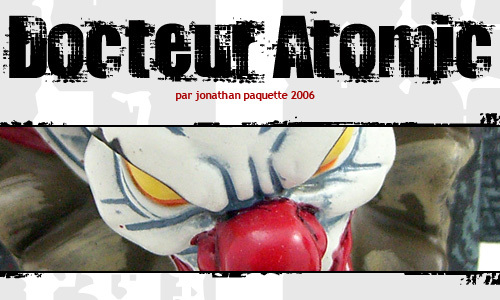
Krój Docteur Atomic od Jonathana Paquette'a uderza jak piaskowany tusz – wyraziste, blokowe litery z poszarpanymi przerwami, wytartymi krawędziami i zużytą teksturą, która sprawia wrażenie industrialnej, a nawet lekko radioaktywnej. To darmowy, erodowany font typu display, którego poszarpana powierzchnia nadaje nagłówkom historii bez potrzeby stosowania dodatkowych efektów postarzania.
Dzięki Docteur Atomic Twoje słowa stają się głośniejsze i bardziej surowe: plakaty koncertowe, ziny, okładki płyt, naklejki na deskorolki, tytuły gier dystopijnych, ostrzeżenia sci-fi czy promocje na Halloween – wszystko to zyska dzięki jego wyrazistemu charakterowi. Używaj go w dużym rozmiarze, dodając nieco więcej światła między literami, aby zachować czytelność erozji, a w tekście głównym połącz go z neutralnym krojem bezszeryfowym – ten darmowy font sam wykona całą pracę.